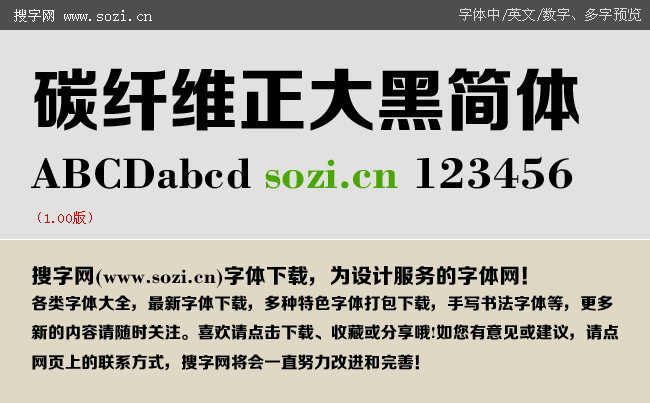
碳纖維正大黑簡體
本字體應(yīng)開發(fā)者方正字體要求已下架,謝謝您的理解與支持!搜字網(wǎng)提供一碳纖維正大黑簡體中文藝術(shù)字體下載,正黑體取傳統(tǒng)黑體結(jié)構(gòu),筆形全部采用平行、垂直與弧度的流線形設(shè)計(jì),簡潔易識(shí)、美觀大方,具有個(gè)性,加之鏡像對(duì)稱的現(xiàn)代構(gòu)成形式,達(dá)到莊重與簡潔有機(jī)融合、設(shè)計(jì)感與閱讀功能兼?zhèn)涞淖罱K效果。適合書籍排版,報(bào)紙排版,海報(bào)設(shè)計(jì),包裝設(shè)計(jì)等廣告設(shè)計(jì)場(chǎng)合應(yīng)用。